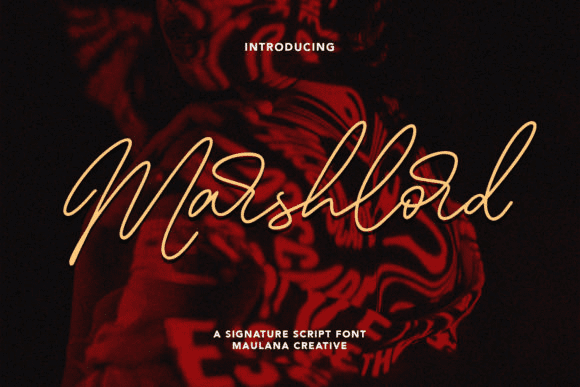
[Creativefabrica] Marshlord Font
Название: Marshlord Font
[Creativefabrica] Marshlord Font
Маршаллорд - красивый и изысканный шрифт.
Он имеет стильный, элегантный и современный вид, который может быть использован для логотипов, брендинга, приглашений, канцелярских принадлежностей, свадебных конструкций, сообщений в социальных сетях, и многое другое!